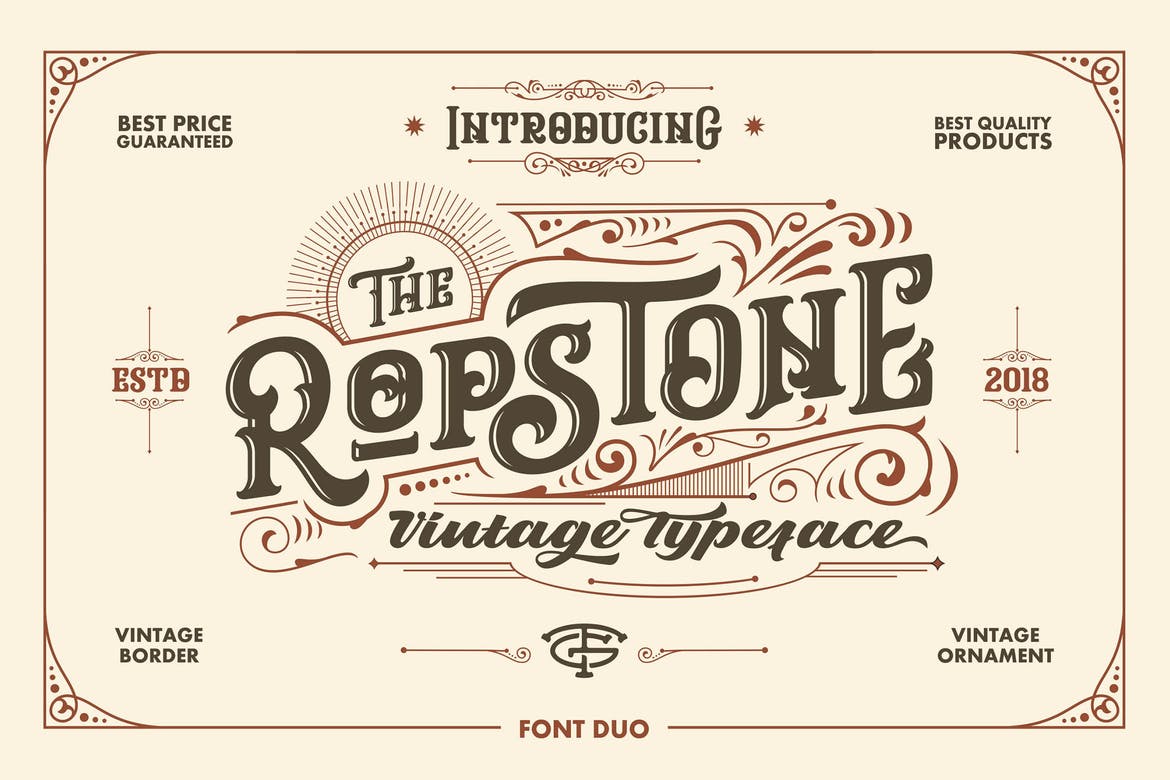
Ropstone è un display di font realizzato a mano, ispirato ai poster classici. Porta la tua passione vintage con questo font, tanta ispirazione mentre ci accedi. Tutti i vantaggi che proverai quando inizierai a creare lavori con i caratteri Robstone. Cosa stai aspettando, il miglior prezzo e la migliore qualità che ti diamo con orgoglio.